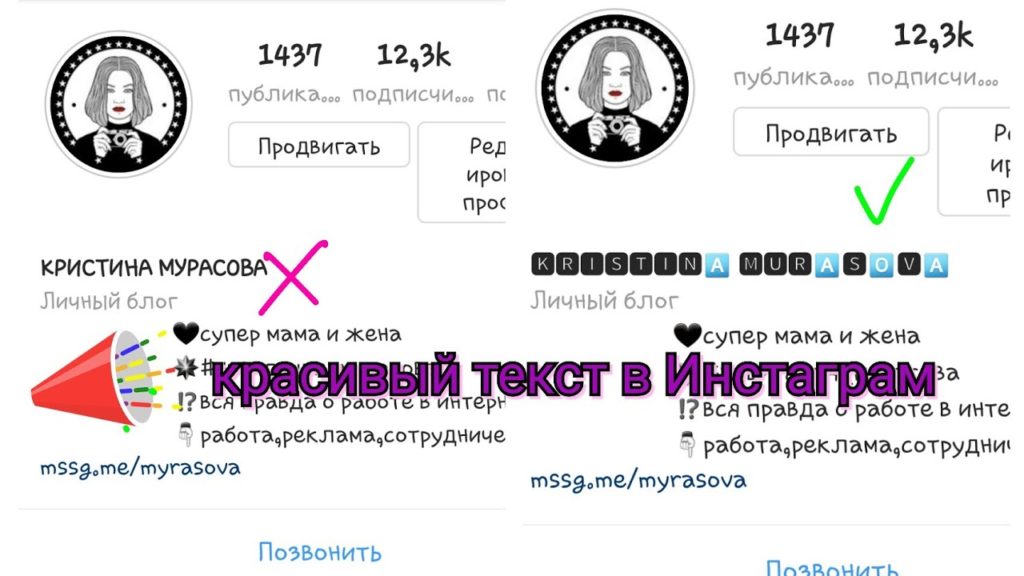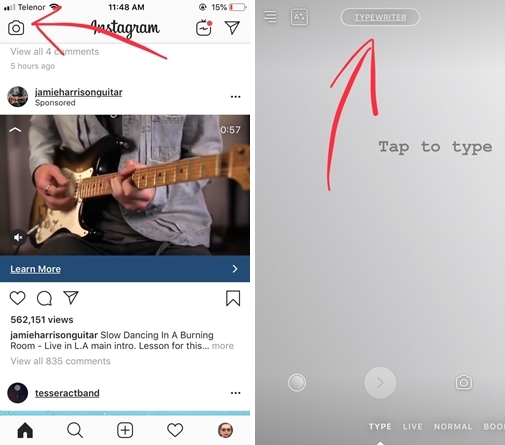
Как изменить шрифт в инстаграме в информации о себе?
Хотите как-то преобразить свои социальные сети? Не знаете, как изменить шрифт в инстаграме в информации о себе? Мы вам подскажем! Сделать это очень просто.
Многие задаются вопросом: как изменить шрифт в шапке инстаграма? И написать там что-то не стандартным шрифтом, а каким-нибудь рукописным курсивом с засечками. У нас есть для вас ответ! Не нужно скачивать каких-либо дополнительных программ и приложений. Всё это делается через обычный сайт.
Как изменить шрифт в шапке инстаграма онлайн:
- Зайти на этот сайт.
- Ввести свои инициалы, имя или ник в верхнем поле для ввода.
- Проскроллить немного ниже, во втором поле будет представлено огромное количество милых и забавных вариантов написания вашего текста.
- Выбрать нужный вариант и скопировать его.
- Перейти в настройки профиля в Инстаграме и вставить надпись.
- Сохраниться! Всё готово! Надпись, написанная оригинальным шрифтом, появится в вашем профиле.
- Вы великолепны!
Раньше в AppStore было доступно приложение Glitch Text (иконка со снеговиком). Оно позволяло проделать подобную процедуру и изменить шрифт в инстаграме в шапке и в поле информации. Но сейчас, к сожалению, программа не доступна для скачивания.
Внимание! Сайт работает только с английской раскладкой!
Значки и смайлики
Как изменить шрифт в инстаграме в информации о себе вы теперь знаете, а как добавить значки, руны? Есть специальный сайт с символами юникода, на котором собрана огромная база символов. Принцип добавления точно такой же: нужно скопировать смайл с сайта и вставить в шапку «о себе» в инстаграме.
В таблице символов Юникода есть огромное множество букв, из которых можно составлять имена на кириллице!
Если вы не можете найти какой-то определенный символ или значок, вбейте в поисковик что-то типа такого: «символ солнца юникод».
Крутые приложения
Если вы не знаете, как изменить шрифт в инстаграме в информации о себе и в шапке, тогда можем порекомендовать вам два крутых приложения.
Они называются Fonts&Text (желтая иконка первая в списке) и Fonts. Скачать их можно бесплатно в AppStore и Google Play.
Функционал приложений достаточно велик. В самих приложениях всё понятно. Как изменить шрифт в инстаграме в информации о себе и сделать буквы и надписи в черном кружочке/круглых рамках или с засечками?
В Fonts&Text сначала нужно выбрать понравившийся шрифт, а затем ввести свою надпись в пустое поле. Всё абсолютно бесплатно. А вот в Fonts придется заплатить некоторую сумму за определенные шрифты.
Помимо различных шрифтов можно создавать милые японские смайлки каомодзи, как вот этот
¯\_(ツ)_/¯ или этот ╰( ͡° ͜ʖ ͡° )つ──☆*:・゚.
Огромную подборку подобных каомодзи можно найти на этом сайте.
Теперь вы знаете, как изменить шрифт в инстаграме в информации о себе. Применяйте этот простой прием и удивляйте своих подписчиков! Пускай ваши фото собирают огромное количество лайков.
как его найти и применить
Наверняка тебе доводилось видеть такой шрифт в шапке аккаунтов или в постах. На него трудно не обратить внимание — жирный шрифт для Инстаграма* действительно выделяет текст, делает его непохожим на другие.
Интересно, что сама система Инсты* не предполагает возможность сделать буквы «толстыми». Но это легко решить при помощи других инструментов.
- 3.1 О себе
- 3.2 В посте
- 3.3 В шапке профиля
- 4 Инструменты для жирного шрифта
- 5 Телеграм-бот
- 6 3 онлайн-сервиса
- 7 Заключение
Зачем и кому может быть нужен жирный шрифт в Инстаграме*
Жирный шрифт для Инстраграма* — отличный способ выделить свой профиль среди остальных. Так как для его создания нужно немного заморочиться, для шапки и для постов его используют не повсеместно. А это хорошая возможность подчеркнуть индивидуальность.
Кому может быть нужен такой толстый вид букв? Всем. Он помогает выделить главную фразу, обратить внимание на конкретный участок текста, сделать акценты, да и в конце концов — это возможность создать красивый пост.
- Подумайте о доступности: что хорошего в классном шрифте, если его трудно читать и некоторые зрители не заметят ваше сообщение? Будьте как можно более инклюзивными и используйте шрифт, приятный для глаз. Подумайте также о технической доступности.
Выберите шрифт, который говорит на том же эстетическом языке для страницы IG, которая имеет целостный общий вид.